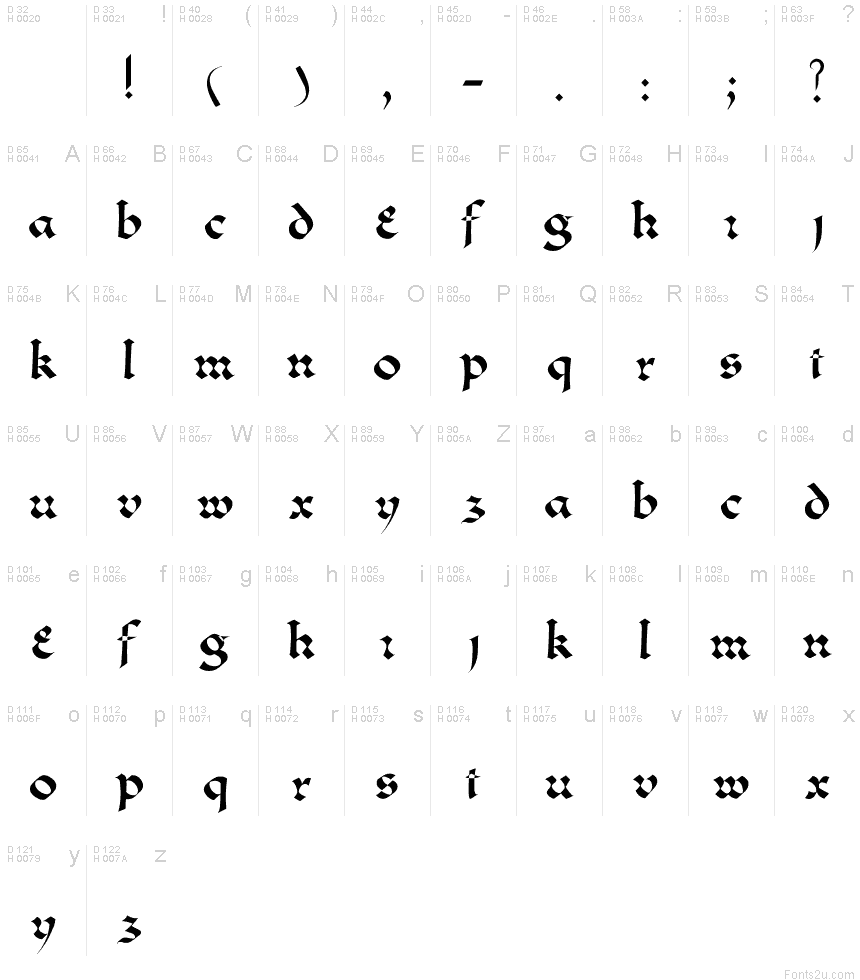
Lombardo to darmowy gotycki font średniowieczny z ostrymi, spiczastymi szeryfami oraz szerokimi, zaokrąglonymi łukami, które przechodzą w kanciaste łączenia. Litery mają rytm przypominający rzeźbiony kamień, z ciemnymi pionowymi kreskami, romboidalnymi łączeniami i wąskimi otworami, co nadaje projektowi charakter formalnego rękopisu.
Lombardo świetnie sprawdza się na okładkach książek, w brandingu fantasy, tytułach plakatów, logotypach, tatuażach i zaproszeniach, ponieważ jego średniowieczna struktura niesie ze sobą silny historyczny ton bez konieczności dodatkowego zdobienia. Lombardo pasuje również do projektów etykiet, nagłówków certyfikatów i opakowań tematycznych, gdy szukasz krojów zakorzenionych w dawnej tradycji gotyckiej.
Lombardo